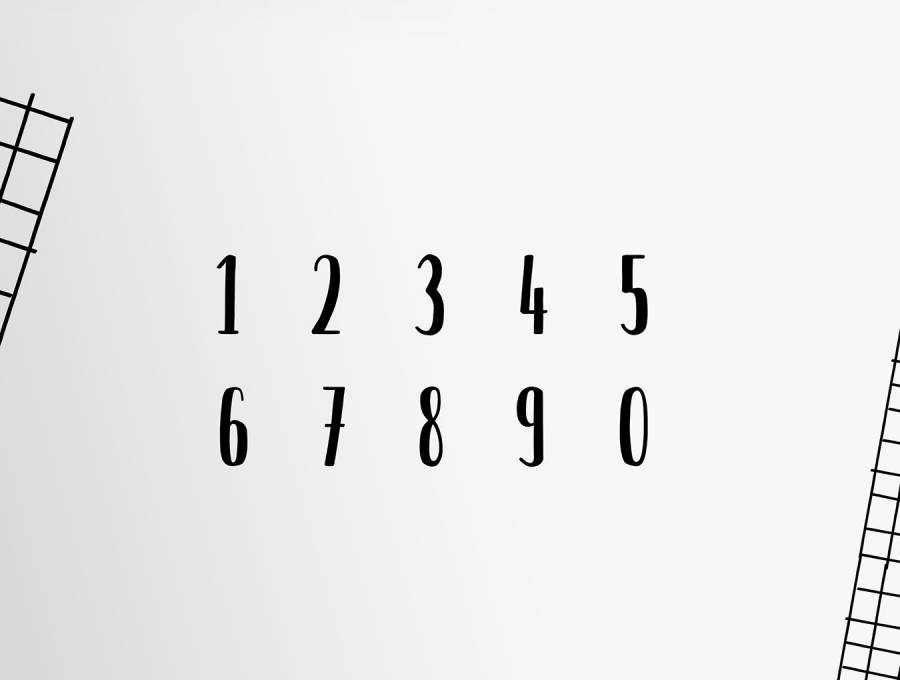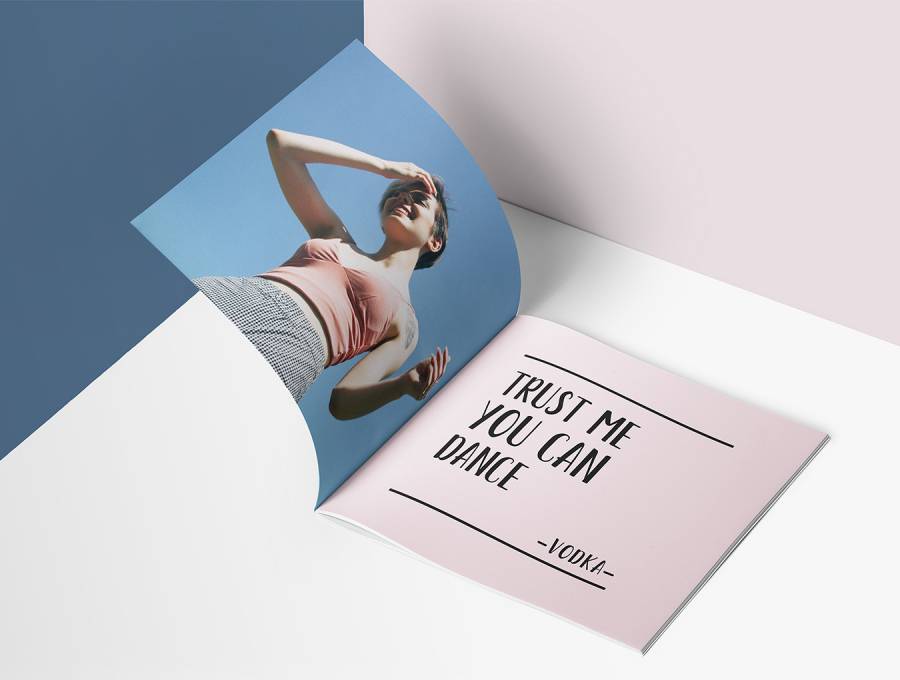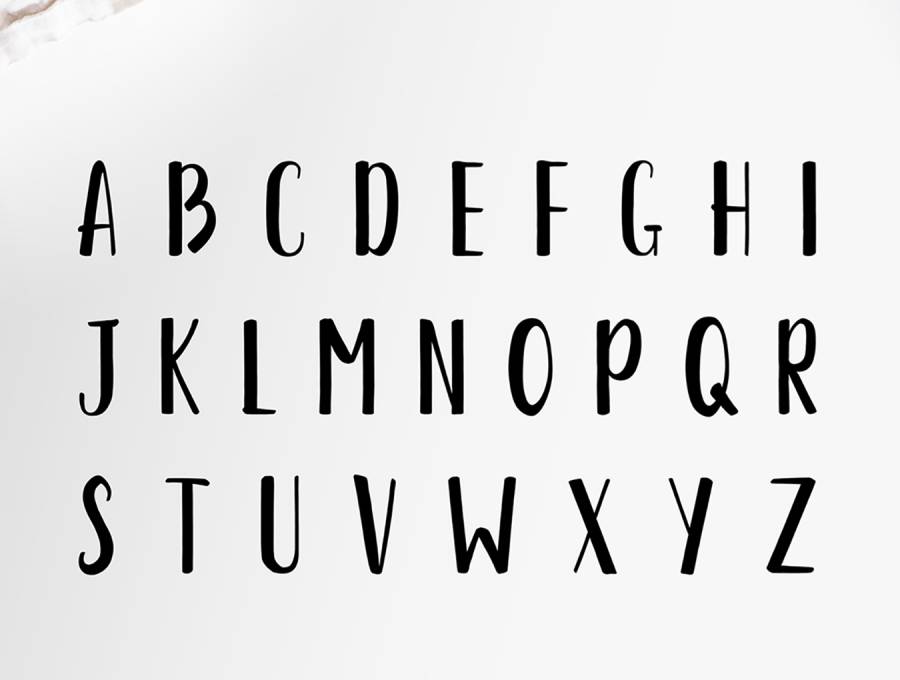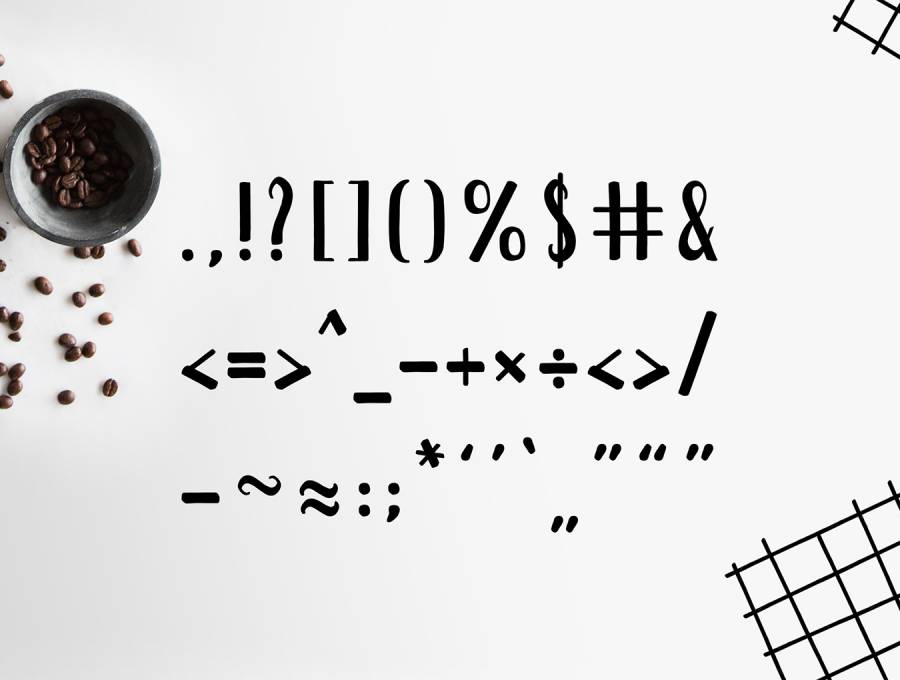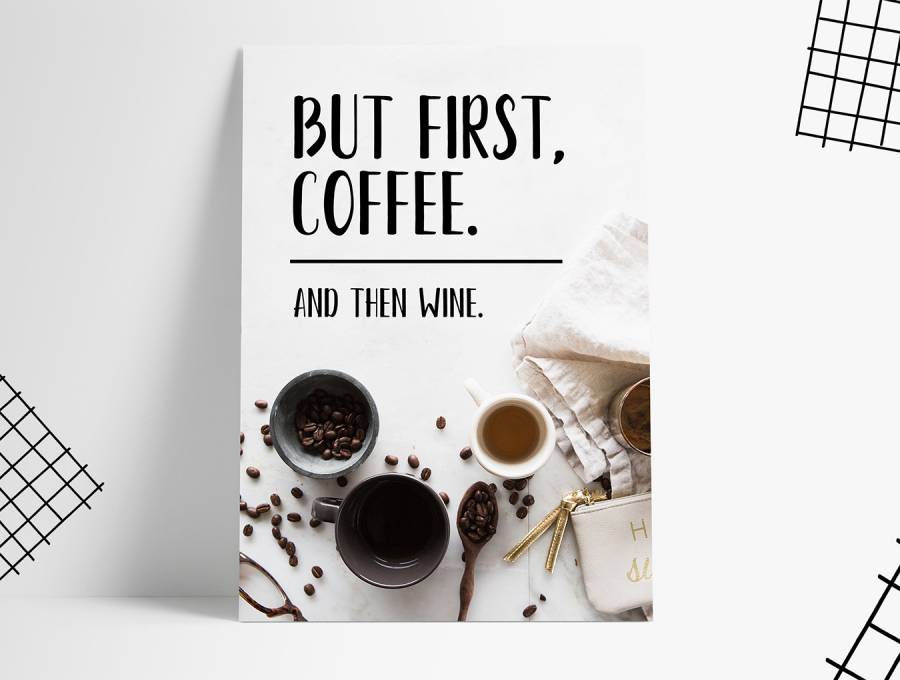
大写几何刷字体,下面有强大的结构。,Austra Brush字体
Austra大写笔刷字体是一种几何笔刷字体,下面有强大的结构。它适用于简短描述,徽标和品牌标识设计,包装,标题等。包括大写字母,数字,符号。文件包括:Austra-Lite.ttf &Austra-Lite.woff。你的WildOnes团队